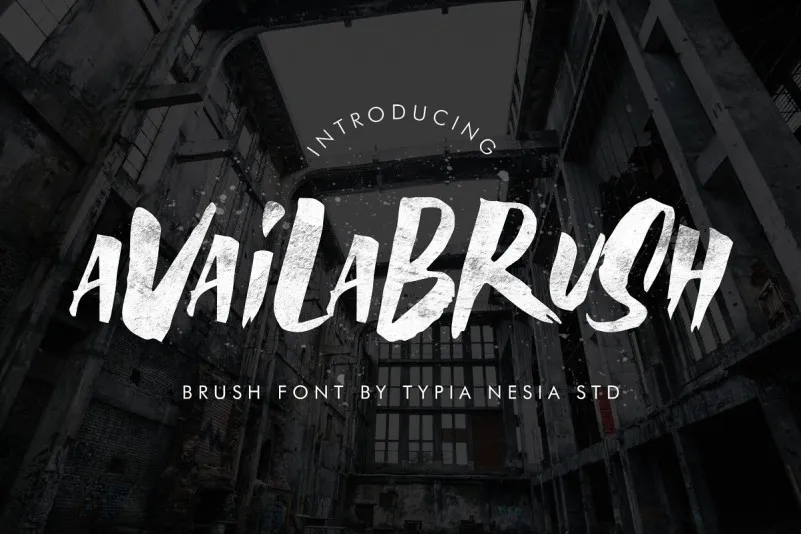
A Availa Brush Font é uma nova fonte feita à mão com técnicas de ferramenta escaneada. Ela carrega a essência de uma escrita manuscrita, oferecendo um aspecto natural e deslumbrante que reflete a arte de escrever por conta própria. Seu estilo livre proporciona um ar de imperfeição, perfeito para adicionar um toque único e autêntico aos seus projetos. Introduzida pela Typia Nesia, Availa Brush é uma fonte real, produzida à mão com um pincel. Você pode misturar as letras maiúsculas e minúsculas e até mesmo os alternativos para criar combinações únicas e atraentes. A Fonte Availa Brush se destaca como ótima opção para diversas necessidades de design, incluindo logotipos, branding moderno, propaganda moderna, livros/capas, cartazes e mensagens inspiradoras, bem como websites/blog, selos personalizados, mangás, poltrona e camisetas. A Availa Brush se torna uma fonte ideal para qualquer projeto que exija a arte de um pincel trabalhado à mão.